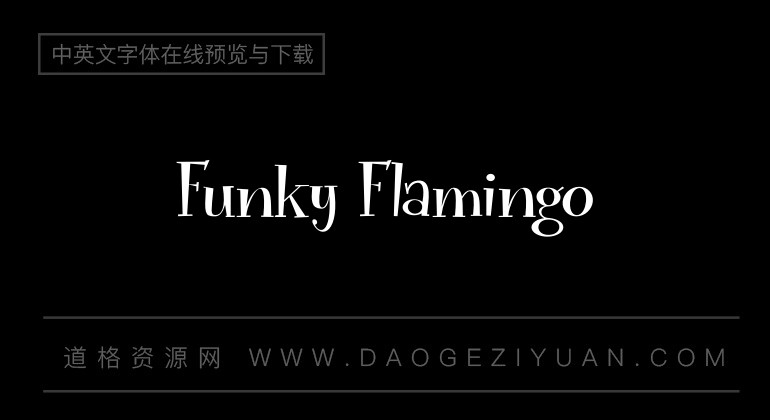
Funky Flamingo
? Funky Flamingo 字体是一款充满活力的手写字体,它具有流行和复古的特点,可以在各种设计中突出重要的文字。它有助于提升设计的视觉效果,并且具有独特的外观和色彩,使您的设计更具个性。它也可以用于创作海报、海报、海报、卡片、标志、标题和网页设计等。
Funky Flamingo是一款非常不错的手写艺术字体,具有很好的视觉感,适合于文化类的宣传设计、商业类品牌的广告和产品包装设计以及个性化文字排版等较多场景。